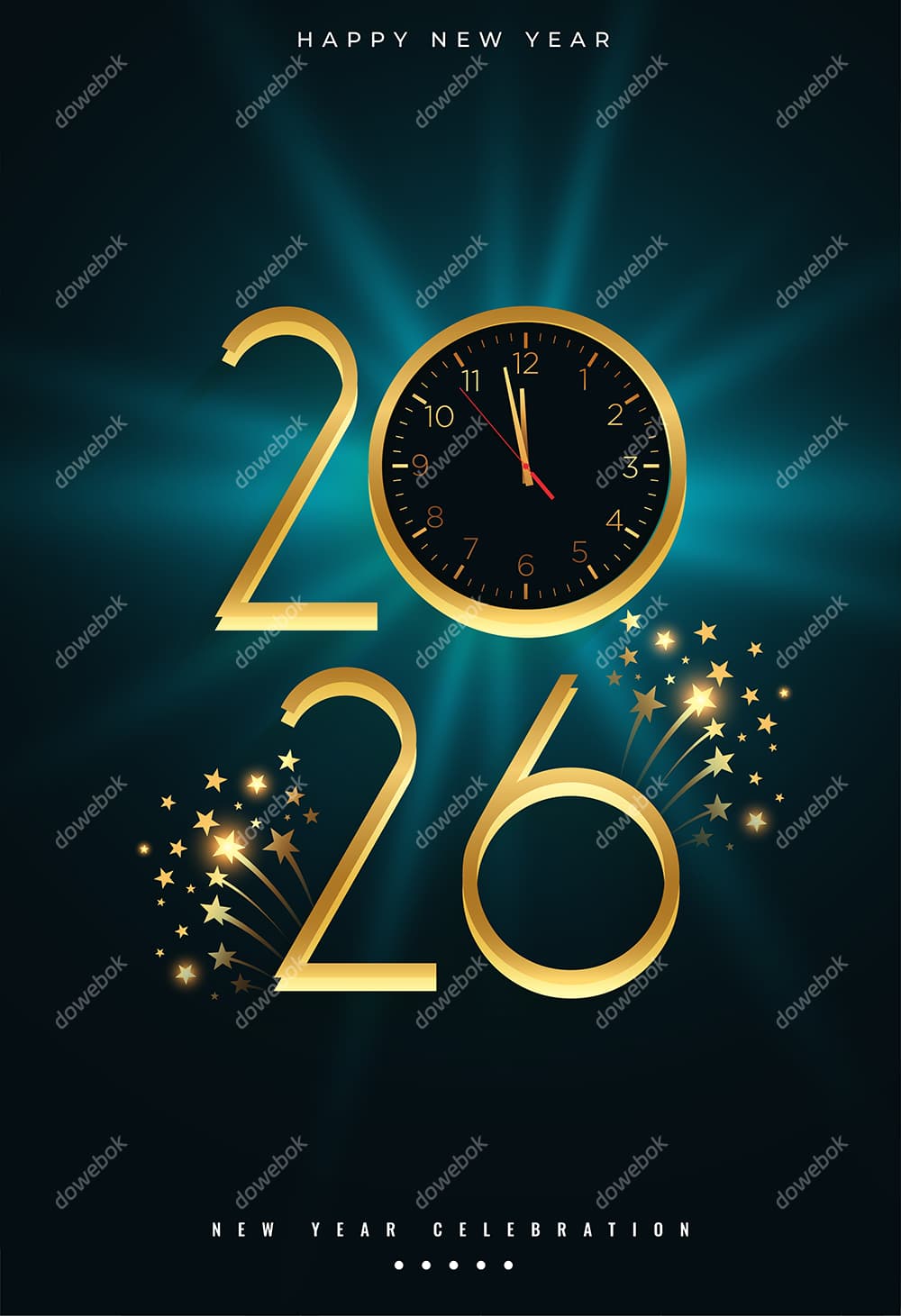
这是一款由黑金时钟和金色数字设计的 2026 新年快乐海报矢量素材,深暗背景衬着蓝调光束,金色 “2026” 字体间嵌着黑金时钟(指针指向新年时刻),周围点缀星芒装饰,上方配 “Happy New Year” 英文。时钟元素呼应跨年节点,金蓝配色既显高级感,又借星芒传递庆典氛围,适配跨年倒计时海报、电子祝福素材,兼具仪式感与视觉张力。